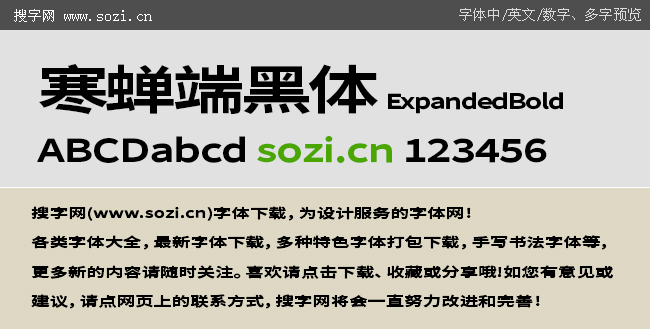
寒蟬端黑體ExpandedBold
搜字網(wǎng)給大家提供一款寒蟬端黑體ExpandedBold中文字體下載,寒蟬端黑體是基于思源黑體進行調整的黑體字體,在原字體風格上重新插值生成,Expanded系列的寒蟬端黑體是思源黑體的寬體版本。適用于標題設計、海報設計、書籍排版以及網(wǎng)頁設計等應用。